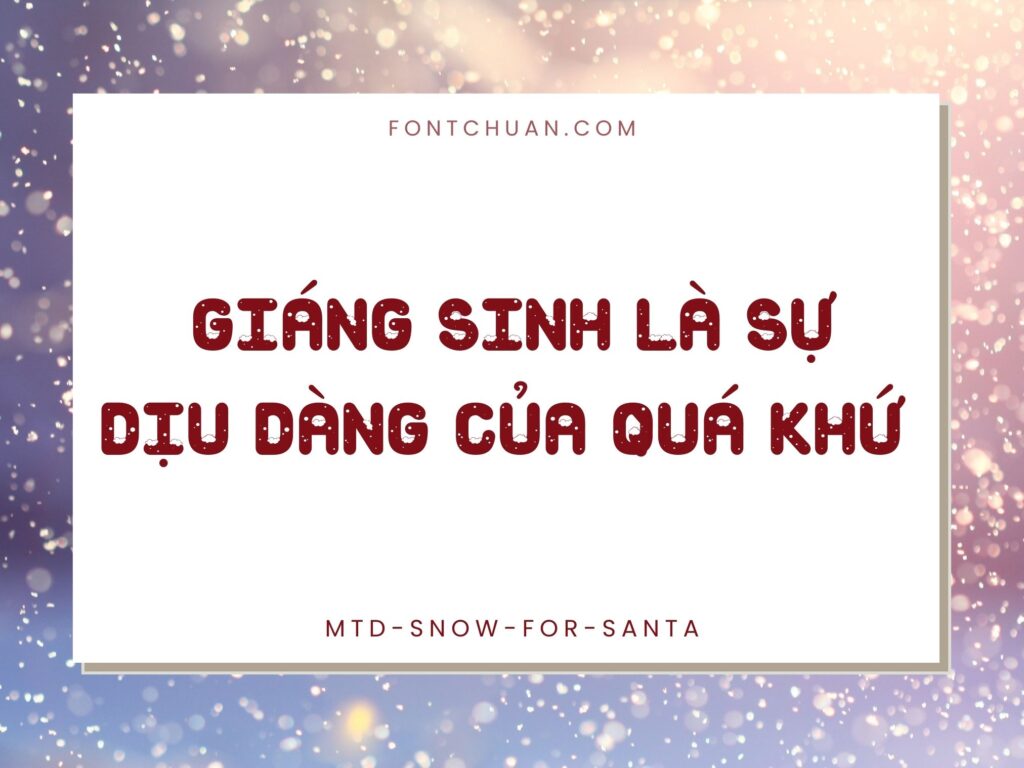
Font MTD Snow For Santa Việt Hóa
Tác giả Font: Dcoxy - Greg Medina
Font MTD Snow For Santa là một kiểu chữ trang trí độc đáo, lấy cảm hứng từ mùa đông và lễ Giáng sinh, được thiết kế bởi dcoxy – Greg Medina và Việt hóa bởi Mộc Hạ. Font này hỗ trợ đầy đủ tiếng Việt cùng hơn 90 ngôn ngữ khác, mở rộng khả năng ứng dụng trong các thiết kế đa ngôn ngữ. Đây là một trong những phông chữ được cộng đồng thiết kế đánh giá cao và sử dụng trong nhiều dự án sáng tạo, đáp ứng nhu cầu đa dạng của người dùng.
MTD Snow For Santa nổi bật với các ký tự được trang trí bằng hiệu ứng tuyết rơi, mang đến cảm giác ấm áp và vui tươi của mùa lễ hội. Font rất phù hợp cho các thiết kế thiệp mời, bao bì sản phẩm, tiêu đề và các ấn phẩm liên quan đến Giáng sinh và mùa đông. Các ngành nghề phù hợp bao gồm quảng cáo, giáo dục, công nghệ, thiệp cưới và ảnh cưới. Font này cũng lý tưởng cho các sự kiện như Tết, Giáng sinh, Valentine và các lễ hội khác.